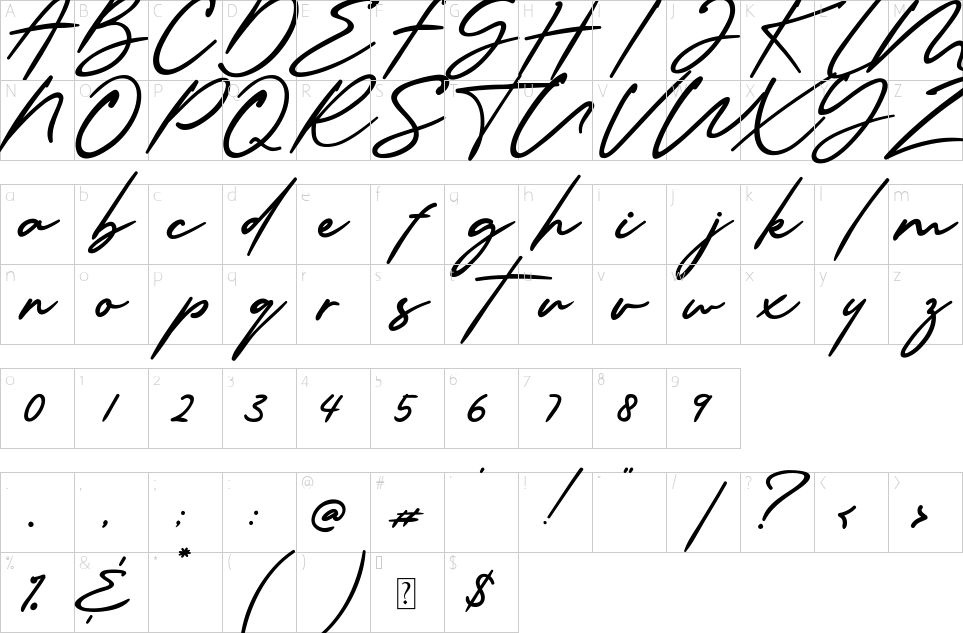
A fonte gratuita ‘Millanova’ é uma escolha perfeita para aqueles que buscam uma fonte moderna e elegante para o seu projeto. Desenvolvida pela Pen Culture, esta fonte foi projetada para aprimorar os textos com um estilo moderno e sofisticado. A ‘Millanova Font’ está disponível tanto para Windows quanto para Mac e já foi baixada 15.959 vezes. Se você está procurando por uma fonte moderna e de alta qualidade, que pode se adequar a diversos tipos de design, esta é uma ótima escolha. Com sua design simples e versátil, a ‘Millanova Font’ é perfeita para o seu próximo projeto gráfico.